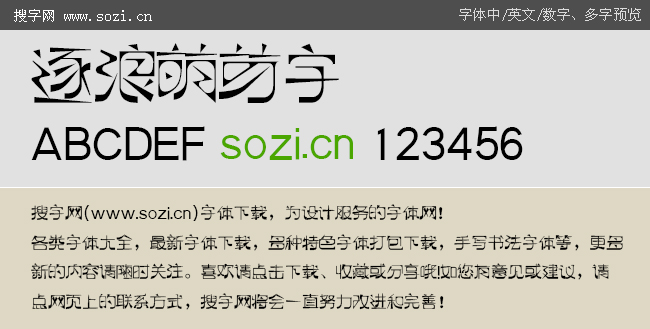
逐浪萌芽字
搜字網(wǎng)給大家提供一款逐浪萌芽字中文字體下載,逐浪萌芽字(Zoomla CMS Fonts)是一款參照《萌芽》月刊的藝術(shù)字體。字體線條呈現(xiàn)外方內(nèi)圓格局,有尖銳的外角、三角部件,而內(nèi)部空間則呈現(xiàn)圓形切割效果,力求體現(xiàn)近代文藝風(fēng)。適用于海報設(shè)計、包裝設(shè)計、廣告設(shè)計等場景。